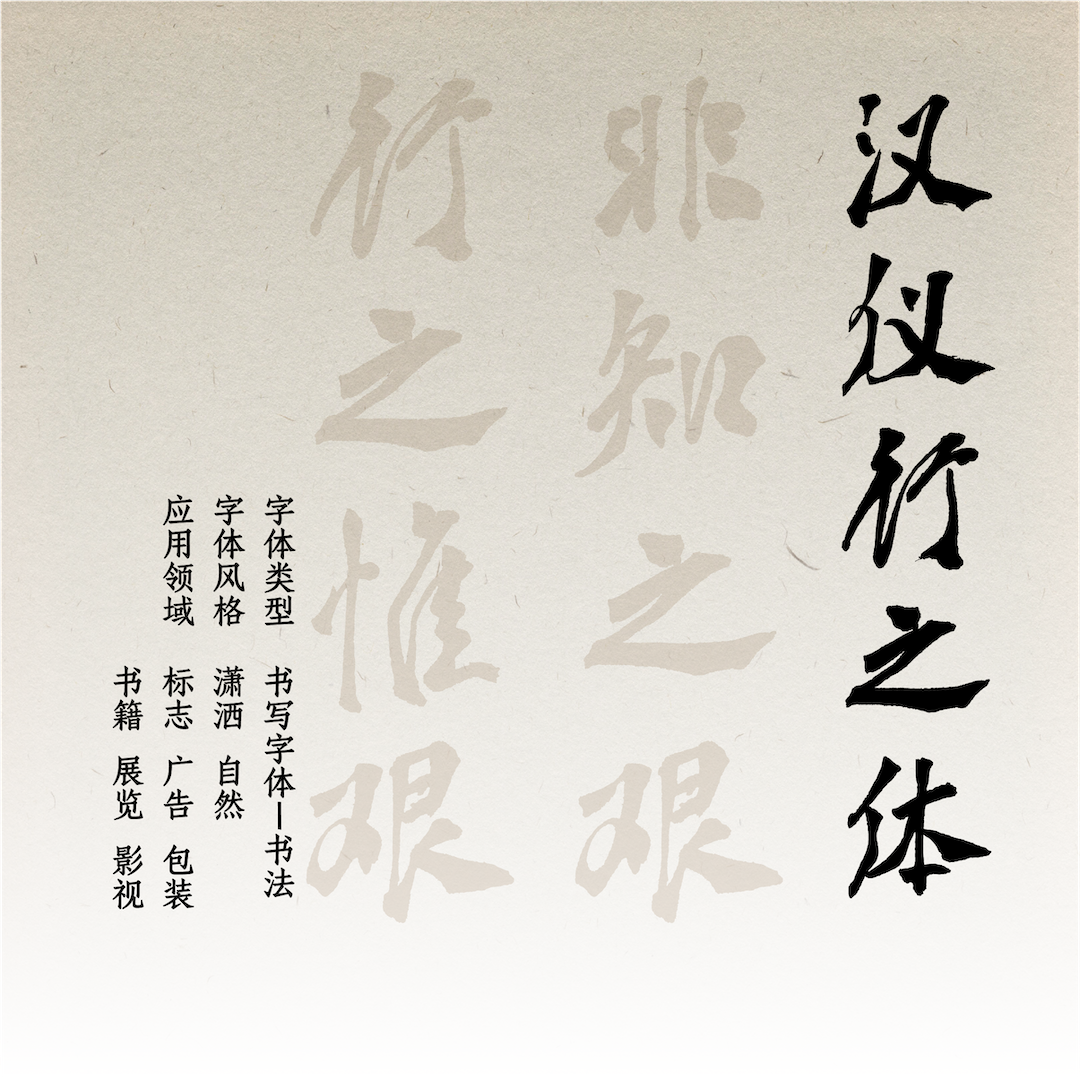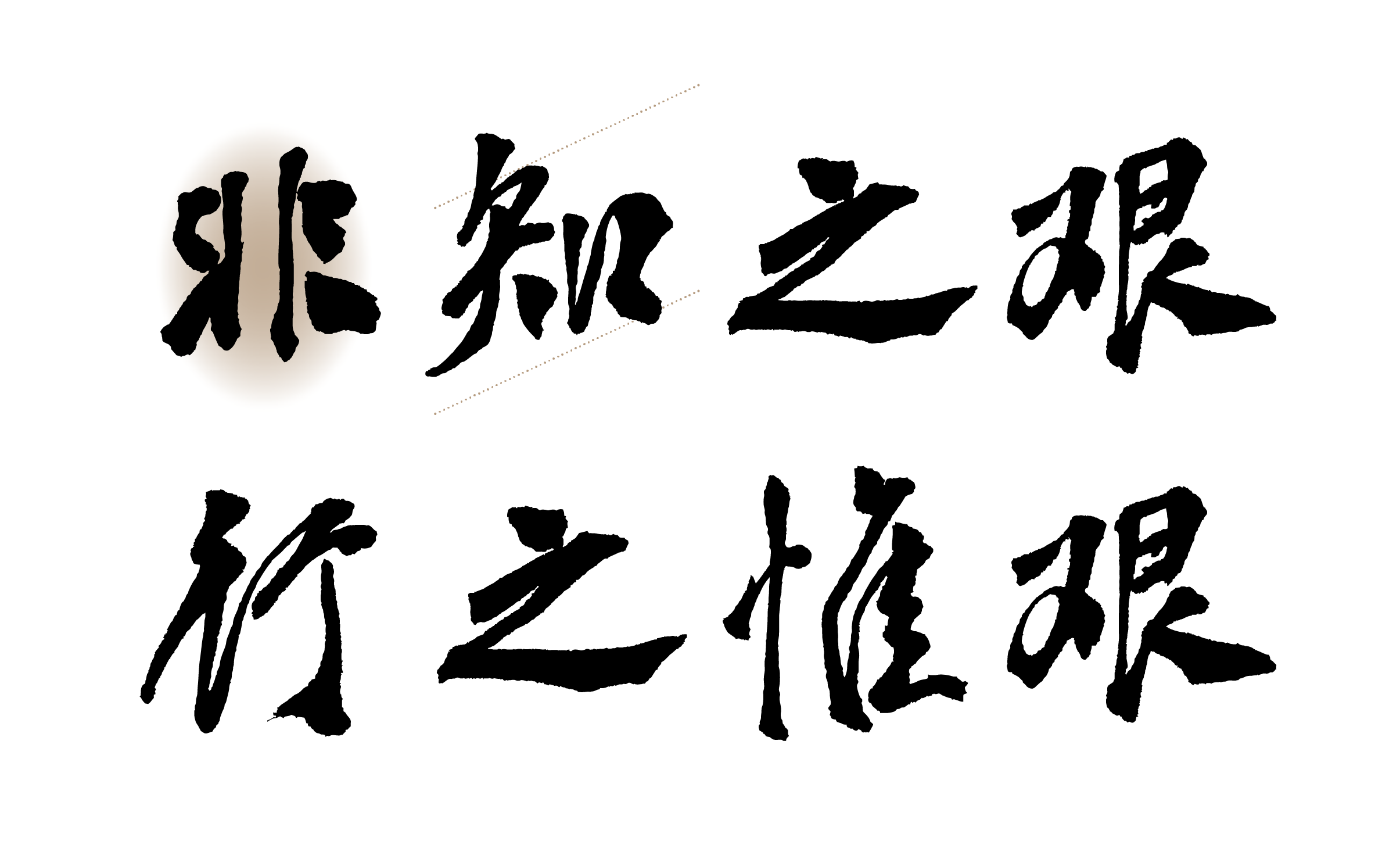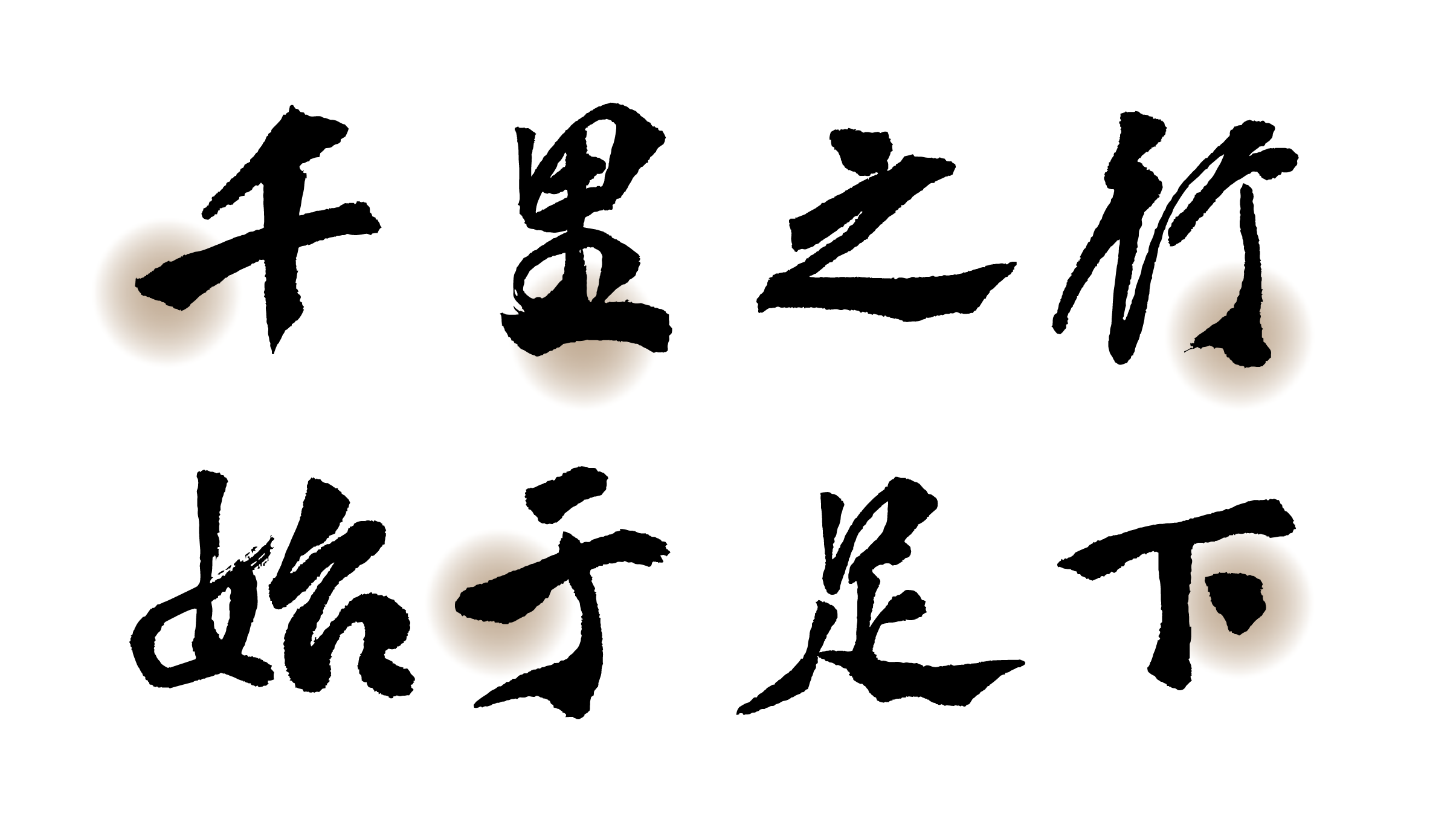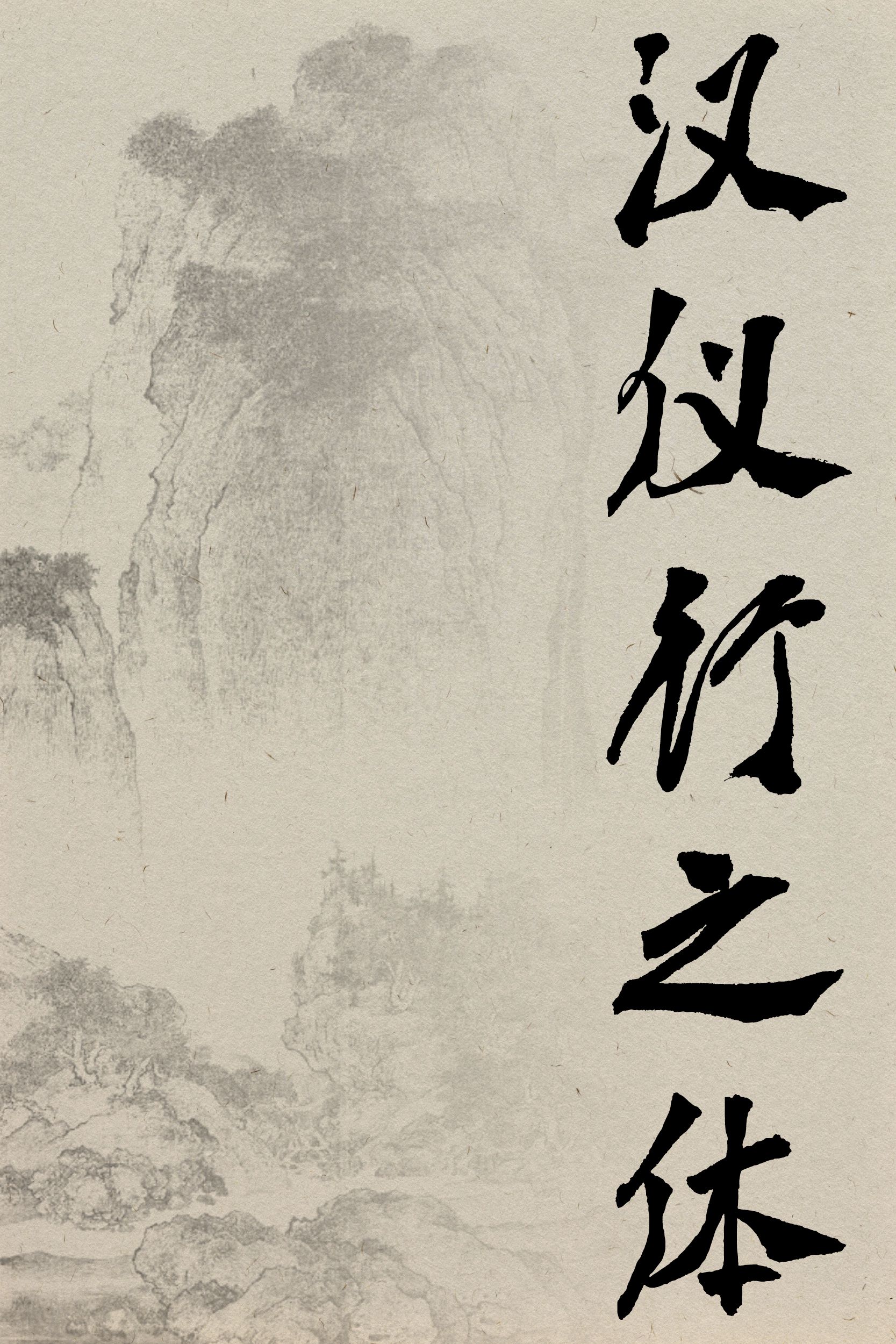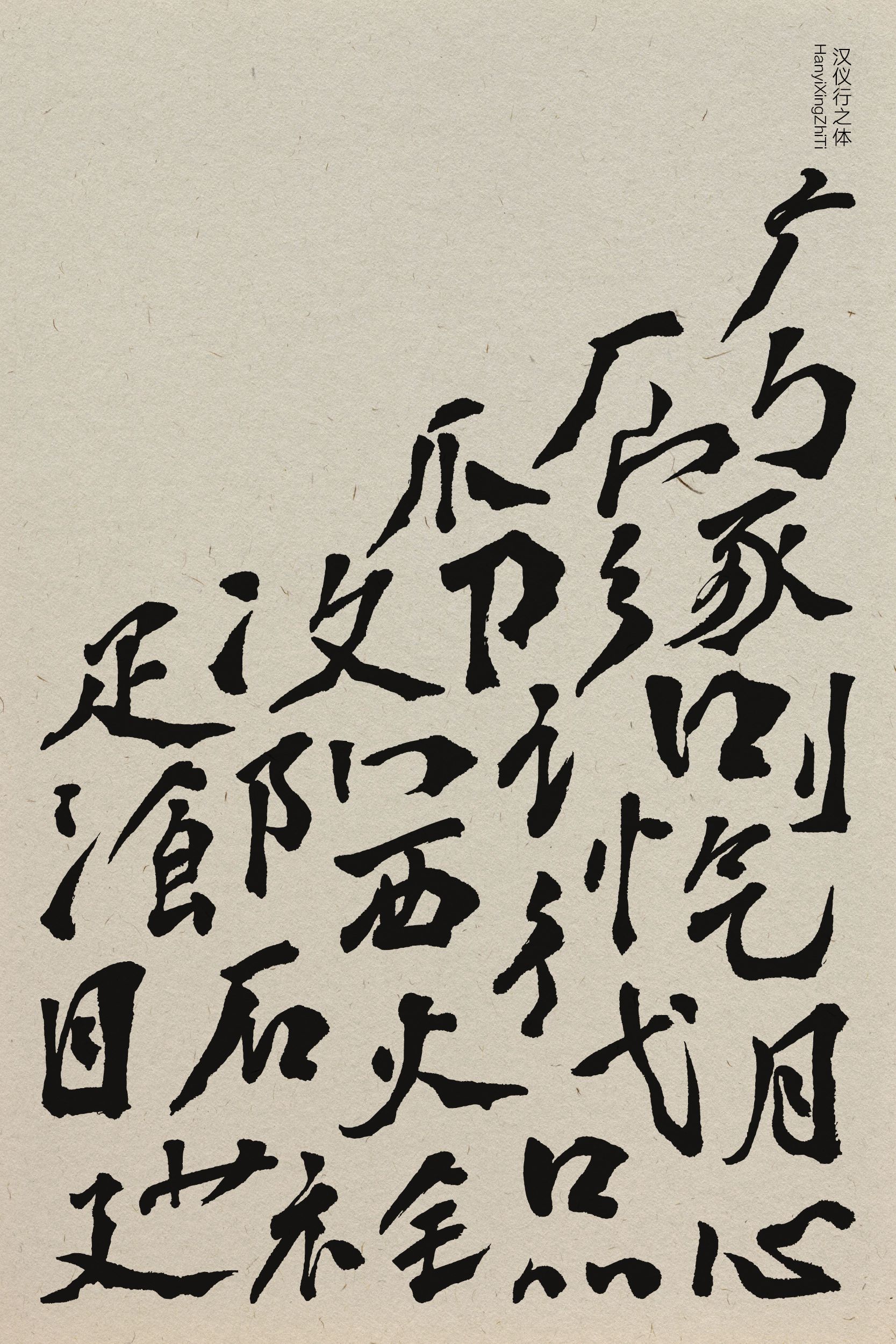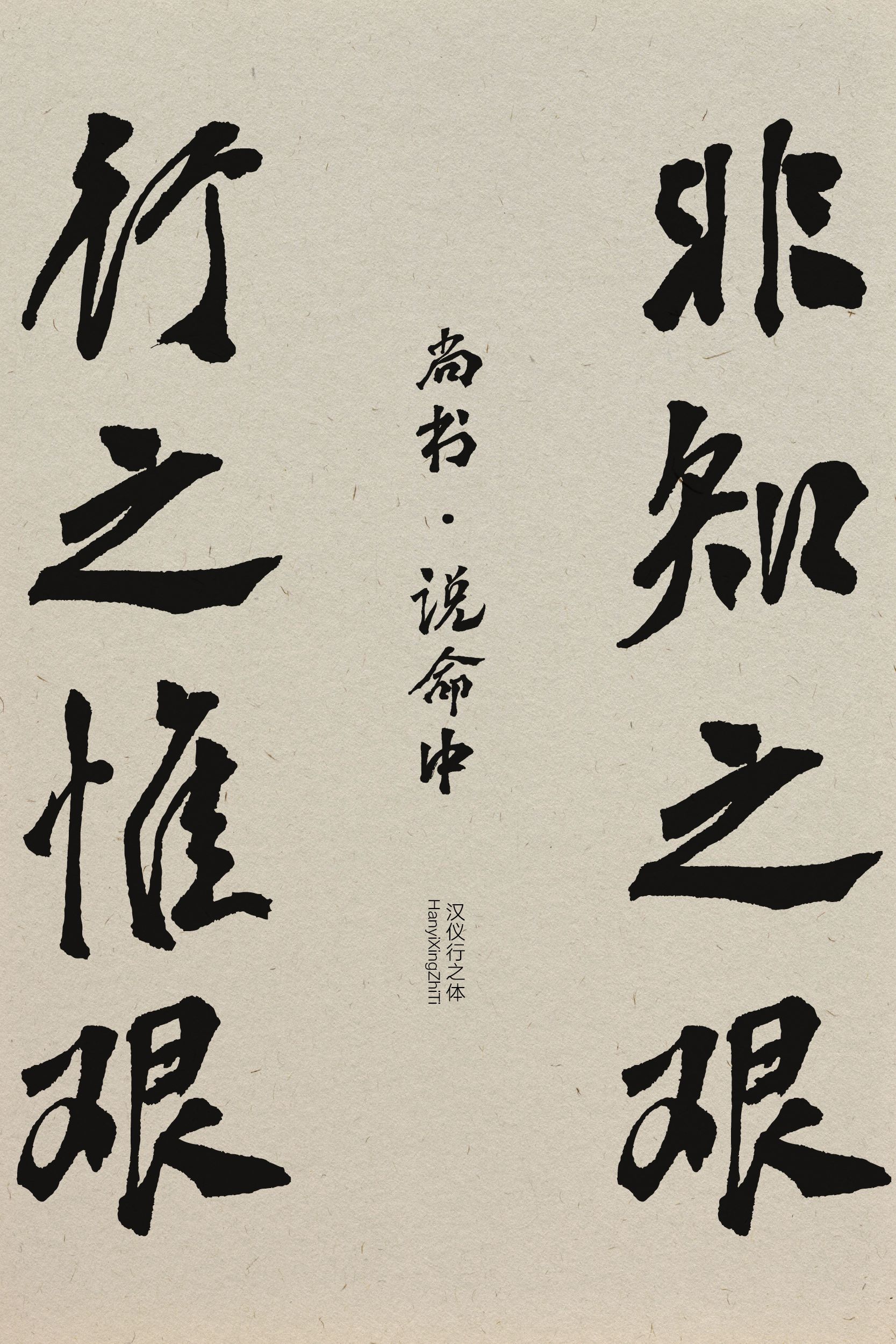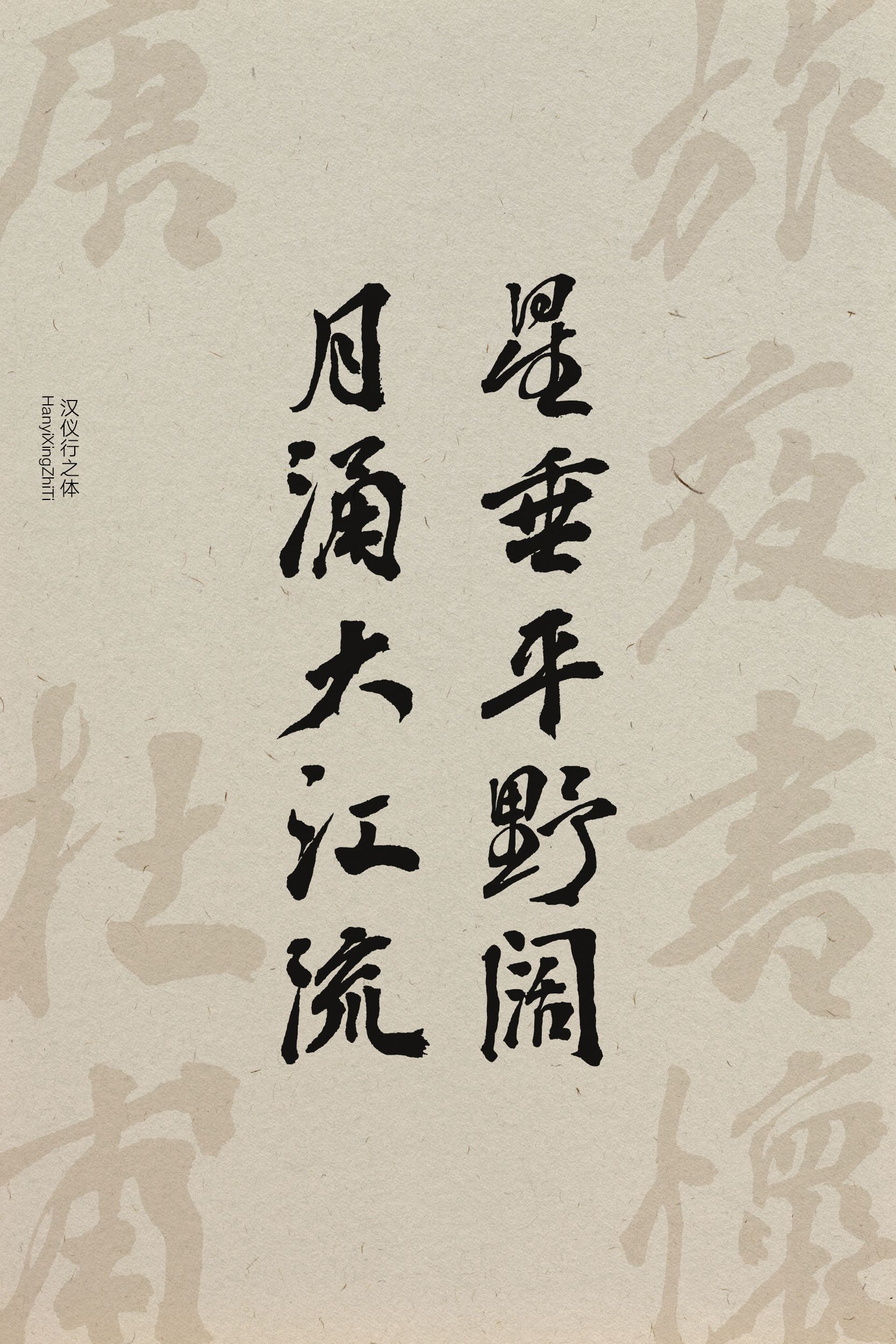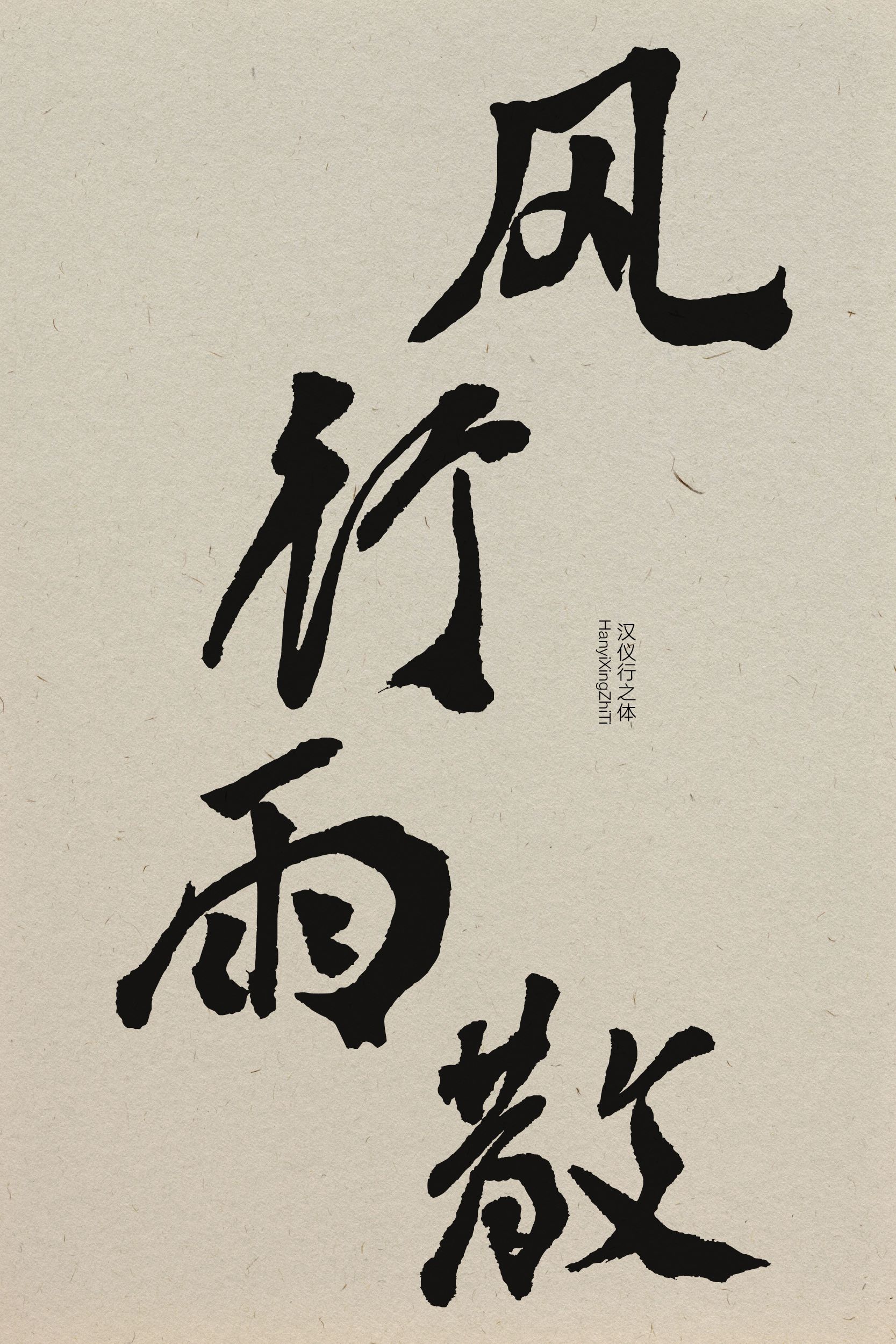
汉仪行之体
汉仪行之体,由汉仪字库签约作者张春晓书写,笔意潇洒,旖旎从风,柔美之中不失力道,洒脱之余不无严谨。这款气质超凡的书法字体适合用于传统节庆、书籍展览、文化艺术等多种使用场景。
汉仪行之体|字体特征
字形舒展而偏长,向右上斜逸出动势。
笔意潇洒,旖旎从风。
柔美之中不失力道,洒脱之余不无严谨。
汉仪行之体|作者介绍
汉仪行之体|字体样张